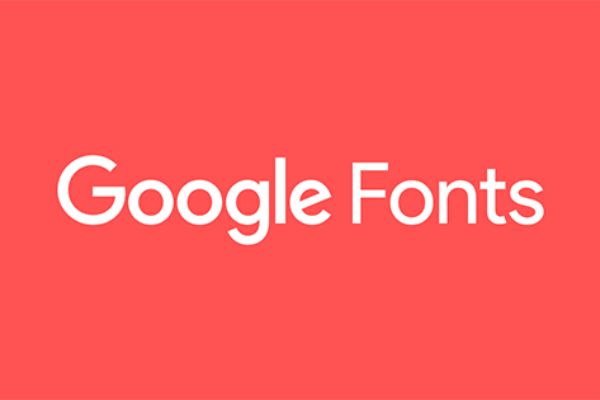
Googleフォントで推奨される文字間隔やフォントサイズ等サイトの見栄えを劇的に改善する5つのポイントを解説
プロとアマチュアのWebサイトを分けるものは「細部へのこだわり」です。 細かなディテールは、時間や労力を要することなく、Webサイトの見た目を圧倒的に変えることができます。
フォントは、このような細かいディテールの1つです。 Webサイトでメッセージを伝える際に、フォントは大きな違いを生むのです。文字デザインを最適化すれば、Webサイトのアクセシビリティ、使いやすさ、読みやすさ、全体的なグラフィックバランスを向上させることができますが、そのためにはWebサイトに合ったフォントを選ばなくてはなりません。
Googleフォントはとても人気があります。Googleフォントをうまく利用しましょう。Webサイトの見栄えを劇的に良くさせることができますよ。
1.フォントの種類を減らす
使うフォントの数は、少なければ少ないほどいいのです。 さまざまな書体を使用してメッセージを強調することができます。 一度にいろいろな書体やサイズを多用すると、レイアウトが崩れてしまいます。また、サイト訪問者にとっても、伝えようとしているメッセージがわかりづらくなってしまいます。
よって、違うフォントを4つ以上(見出しやページのタイトル、本文、サブタイトル、引用符には1種類ずつで)は使わないようにしましょう。Webサイトが素人っぽく、ごちゃごちゃして見えてしまうからです。 本文とサブタイトルに同じフォントを使うのがよく、無理に違うフォントにする必要はありません。
しかし、サブタイトルのフォントを変えると、目につきやすくはなります。 また、フォントの書体は最大でも2種類に制限し、Webサイト全体でも守るようにしましょう。
複数のフォントを使用する場合は、文字幅に基づいて合うものを選択してください。
たとえば、VerdanaとGeorgiaの組み合わせでは、似たような値で調和のとれたペアができます。 このペアと、ImpactとBaskervilleのペアを比較してください。ここでは、Impactで書かれた単語がBaskervilleで書かれた単語を覆い隠してしまうのです。
2.標準フォントにする
Googleには魅力的なフォントがあり、Webサイトのデザインをフレッシュに、新しく、今までになかったようにに見せることができます。どのフォントデザインも味があり、Webサイトが違う印象になります。多くの人は新しいフォントを選ぶのに夢中になってしまいがちです。
でも、Webサイトの訪問者は新しいフォントは慣れていないのでとても読みにくいと思うかもしれませんので、Open Sans、Georgia、Loraなど、人々がよく親しんでいるフォントをにするようにしてください。
ブランド戦略のためにWebサイト運営でもしていない限り、フォントをカスタマイズするのではなく、標準フォントにしてプロらしく見える方にした方が良いでしょう。
また、Web開発者が直面する大きな問題の1つに、見出し、サブタイトル、本文、引用などのコンテンツにどの書体を使えばいいのかわからないということがあります。
メインコンテンツの書体の選択は、見出しやロゴの場合とは異なり、コンテンツの主な目的は、商品やサービスに関する有用な情報を読者に提供することです。 Calibri、Arial、Trebuchetなどのフォントデザインを選ぶようにしましょう。
3.行間に適切なスペースを入れる
コンテンツを読みやすくするには、各行の間に適切なスペースを入れましょう。文字体裁では、行のスペースを表す「レディング」や「行の高さ」という用語があります。行の高さを増やせば、行の間の文字の白いスペースも増えて、読みやすくなります。
Web開発者にとって、どのくらいの幅にするかを決めるのは困難です。一般に、読みやすくするためには、行の高さはフォントサイズの正確に150%(ぴったりの数値)にするるのが良いでしょう。
この割合を下げたり上げたりすると、それぞれスペースが少なすぎたり、広すぎたりします。たとえば、フォントサイズが24ピクセルの場合、行の高さは36ピクセルになります。これは24ピクセルの150%です。
2行の間に適切な空白を入れると、理解度が最大で20%向上することが証明されています。空白をいれるのは、見やすいコンテンツをユーザーに提供するためなので、無駄な部分は削除してしまいましょう。
4.適切なフォントサイズを選択する
ユーザーはさまざまなデバイスからWebサイトにアクセスします。
つまり、コンテンツはデバイスのあらゆるサイズと解像度に対応している必要があります。したがって、ユーザビリティと読みやすさを維持するためには、複数のデバイスでうまく動作するサイズにすることが重要です。
好きなフォントサイズを選択できるからといって、見出しやタイトルをまちまちのサイズにしないようにしましょう。サイト訪問者が見やすいく調和のとれたサイズを選択するようにしてWebサイトをまとまりのあるものにしましょう。
さらに、見栄えを気にするあまりフォントサイズを自分で細かく設定するのではなく、標準フォントサイズを使用しましょう。数学モデルに基づいて推奨されるフォントサイズには、8、16、24、32、48、64、95があります。
段落の読みやすさを向上させるには、メインコンテンツには16ピクセルのフォントサイズを使用することをお勧めします。これらのガイドラインに従えば、バランスの取れたフォントサイズになります。
5.テキストと背景は適切なコントラストにする
Webサイトは、テキストと背景の色が似ていると、読む人が混乱してしまいます。訪問者には提供する情報に集中してもらわなくてはなりません。そのため、コンテンツをより見やすくするために、必ず対照色を選びましょう。
W3C(World Wide Web Consortium)によると、画像テキストと小さい文字の本文のコントラスト比は、背景に対して4.5:1でなければなりません。一方、大きな文字(14〜18ポイント以上)の場合は、背景に対して3:1のコントラスト比が理想です。色を決めた後、実際の画面でもチェックしてみましょう。
洗練され、優雅で、美しい印象を与えられるようにシンプルな色にしてください。ユーザーが肝心な情報に集中することができます。背景と対照的になるような基本色は、安っぽくなく重要なコンテンツを目立たせることができます。また、ネオンカラーは目に負担をかけてしまうので使用は避けてください。
Googleフォントを使用してWebサイトを最適化し、大幅な変更を加えることなくユーザーフレンドリーにするためのヒントをいくつか紹介しました。こういう小さな違いがWebサイトに有益な改善をもたらすものです。試してみて、違いを感じてみましょう。